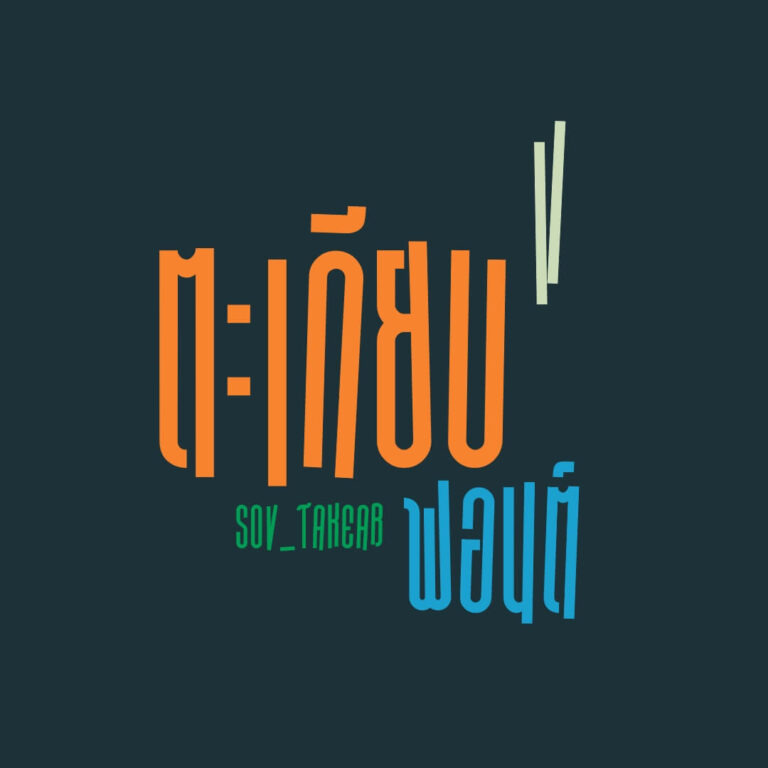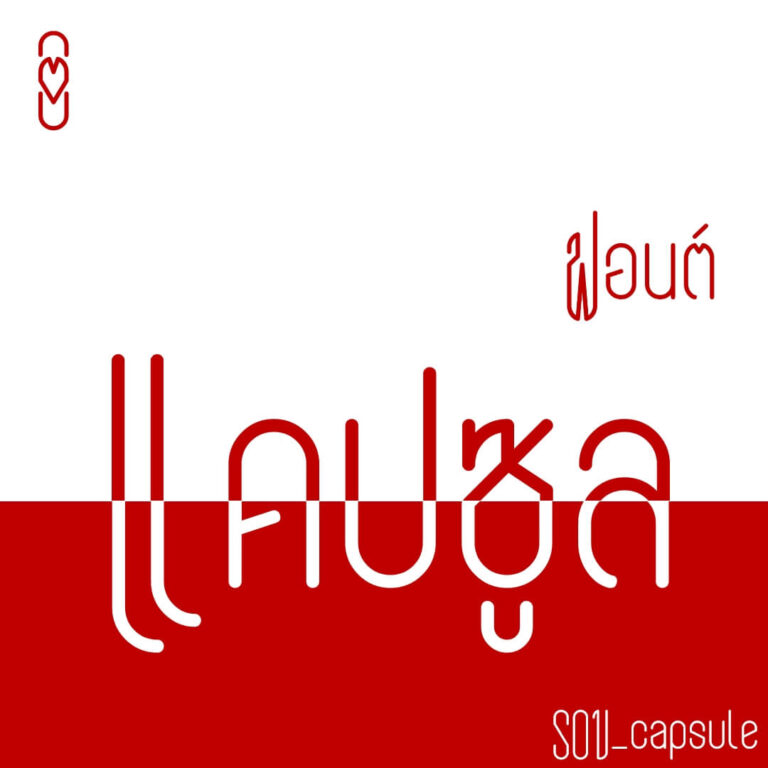
เอฟซี ซาวน์ ราวด์ (FC Sound Rounded)
The Seeing (Sweet) Sound เสียง (หวาน) ที่มองเห็น พัฒนาต่อจากฟอนต์เอฟซี ซาวด์ เกิดเป็นเสียงที่หวานมากยิ่งขึ้นมาพร้อมน้ำหนัก 10 ระดับ และตัวเอนของแต่ละตัว
ฟอนต์ Bobby (บ๊อบบี้) ฟอนต์ตัวน่ารักๆ ตัวโค้งมีหัว มองไปทางไหนก็มีแต่คำว่าน่ารักเต็มไปหมด ใช้เพื่อเพิ่มความน่ารักของงานต่างๆ ให้น่ารักขึ้นไปอีก แจกฟรีไปเลยเวอร์ชันทดลอง : แบบปกติ 1 น้ำหนัก ใช้ได้เฉพาะแบบส่วนตัว เช่น ใช้ในการศึกษา ใช้จด ใช้ตกแต่งสมุดโน้ตตัวเอง
ฟอนต์ตะเกียบ แท่งตรงยาวมาเป็นคู่ ยาวเท่ากันแต่ไม่เคยเท่ากัน วางแล้วขนานกันแต่ไม่ขนานกัน เหมือนเป็นระเบียบแต่ไม่เป็นระเบียบ
จะเรียกว่า..ต้นแบบมาจากโลโก้แบรนด์ นลินเฟี้ยว ก็ไม่ผิด ดังนั้นฟอนต์ม้วนหัวจึงเป็นแนวโลโก้ฟอนต์ อักษรเด้งๆ เหมาะกับคำสั้นๆ
ฟอนต์ทรงแคปซูล ตัวแรกสูงกว่าใคร ..แค่นั้นเลย
ฟอนต์ Hioly (ไฮโอลี่) ฟอนต์ตัวหนาอ้วนนิดๆ ตุ๊มุๆ >><< ใช้เพื่อเพิ่มความน่ารักของงานต่างๆ ให้น่ารักขึ้นไปอีก แจกฟรีไปเลยเวอร์ชันทดลอง : แบบปกติ 1 น้ำหนัก ใช้ได้เฉพาะแบบส่วนตัว เช่น ใช้ในการศึกษา ใช้จด ใช้ตกแต่งสมุดโน้ตตัวเอง
ฟอนต์ MiGrape แนวหัวทึบ สไตล์ลายมือ อ่านง่ายสบายตา ใช้งานได้ในหลากหลาย ทั้งงานแต่งภาพ งานเอกสาร ทำโน้ตสรุป
ฟอนต์ Goody (กูดดี้) ฟอนต์ตัวแข็ง น่ารักๆ แจกฟรีไปเลยเวอร์ชันทดลอง : แบบปกติ 1 น้ำหนัก ใช้ได้เฉพาะแบบส่วนตัว เช่น ใช้ในการศึกษา ใช้จด ใช้ตกแต่งสมุดโน้ตตัวเอง
ฟอนต์ กรุบกรอบ แบบอักษรที่ใช้เส้นตรงเป็นหลักในการออกแบบโครงสร้างอักษร มีการเอียงเส้นแนวตั้ง (Stem) เล็กน้อย
พีเค เลย ฟอนต์ลายมือน่ารักๆ ตัวอวบๆ เป็นลายมือในตอนที่เขียนค่อนข้างเร็วแต่เขียนแบบตั้งใจ ทำให้ตัวค่อนข้างมีระเบียบ อ่านง่าย ไม่ค่อยหวัด ออกแนวน่ารัก และมีปลายที่มนทู่ แบบไม่ได้กลมบ๊อก มี 5 น้ำหนัก Variable สามารถปรับน้ำหนักแบบ custom ได้
ผลงานฟอนต์ที่ตัว 7 ชื่อฟอนต์ ขมังเวทย์ เป็นชุดอักษรไทยโบราณ